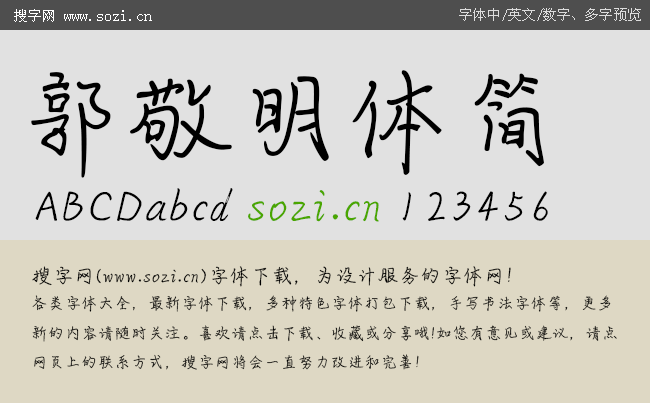
郭敬明體簡手機(jī)字體包
搜字網(wǎng)給大家提供一款名人手寫風(fēng)格手機(jī)中文字體郭敬明體下載。此款字體由郭敬明親手書寫聯(lián)合漢儀字庫出品,漢儀郭敬明體整體風(fēng)格簡約優(yōu)雅、清新灑脫,筆畫清晰而隨意,非常有個性易于辨識。適合喜歡手寫書法字體的朋友在手機(jī)上安裝使用。